10 款最适合编程的字体
编程需要什么样的字体?什么样的字体适合编程?首先字体是要免费的!其次这种字体能够轻松的区分<code>0O</code>并且<code>1lI</code>,避免有用这些字符的混淆而引起程序的bug。还要字体要好看,容易阅读等。
1. Hack
Hack 是基于 Bitstream Vera 和 DejaVu 项目的开源字体,0O并且1lI清晰可辨,字体易于阅读。
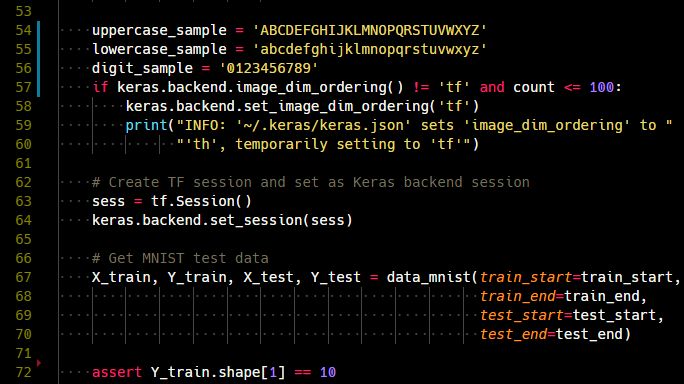
Hack
▎2. DejaVu Sans Mono
DejaVu 也是一款优秀的免费许可字体,来自 Bitstream Vera。能明显地区分0O和1lI。0与 Hack 相比,内部的点有点小,但总体上这个字体还是让人感觉舒适的。
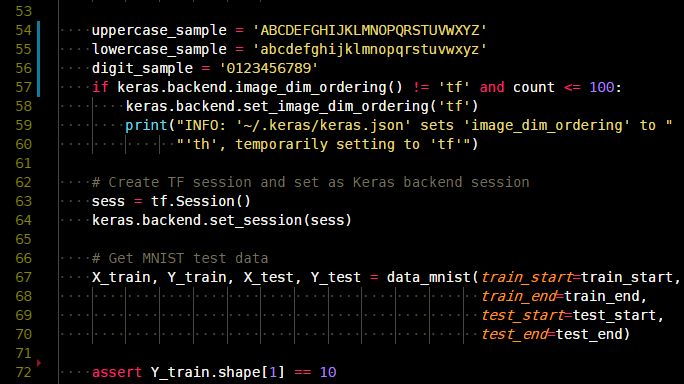
DejaVu Sans Mono
▎3. Monaco
OS X 之前的默认字体就是它,它的风格特殊,有种苹果味。
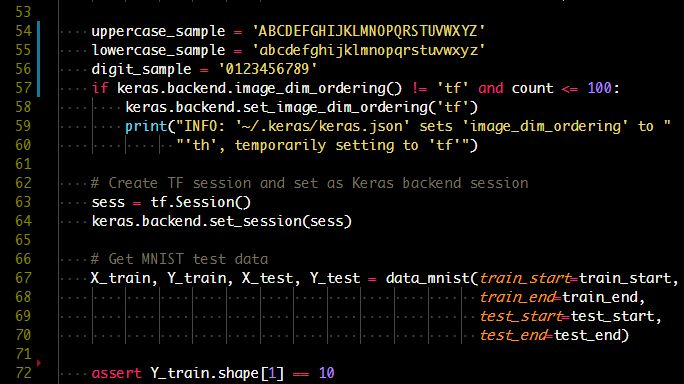
Monaco
▎4. Source Code Pro
Source Code Pro 由 Adobe 设计。整体而言,这种字体看起来比其他字体更清晰。
Source Code Pro
▎5. Menlo
Menlo 之前是 Xcode 中的默认字体,是 DejaVu Sans Mono 的衍生品。在 macOS High Sierra 中,默认字体已更改为 San Francisco Mono
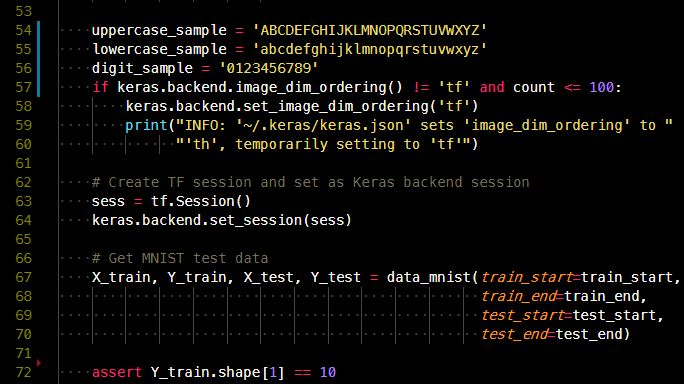
Menlo
▎6. Consolas
Consolas 是 Microsoft Visual Studio 的默认字体,随 Windows 一起提供。
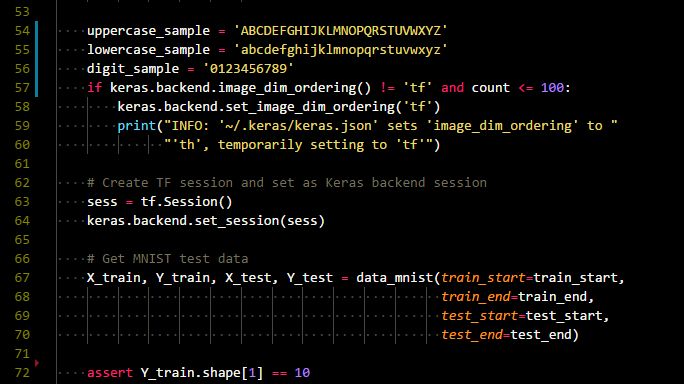
Consolas
▎7. Space Mono
一款优秀的等宽字体,由 Colophon Foundry 设计。
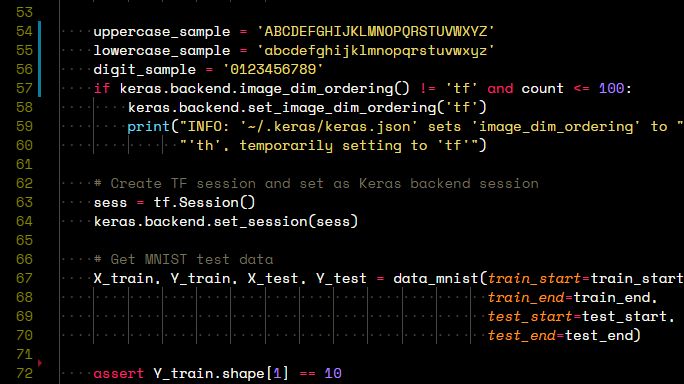
Space Mono
▎8. Anonymous Pro
这个字体给人一种古典打字机的感觉。
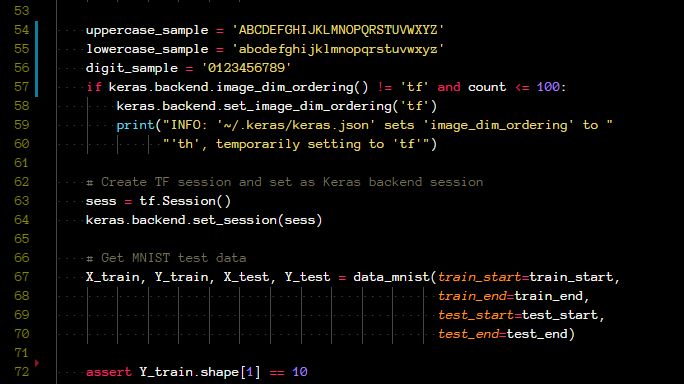
Anonymous Pro
▎9. IBM 3270
IBM 3270 基于 IBM 在 1971 年制造的 IBM 3270 终端中使用的字体,有种复古编程的味道。
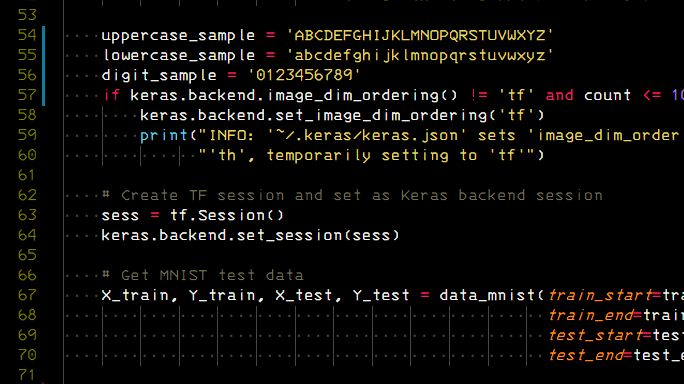
IBM 3270
▎10. Droid Sans Mono
这是为 Android 设计的一种字体,很漂亮,但是0和O并没有区分。
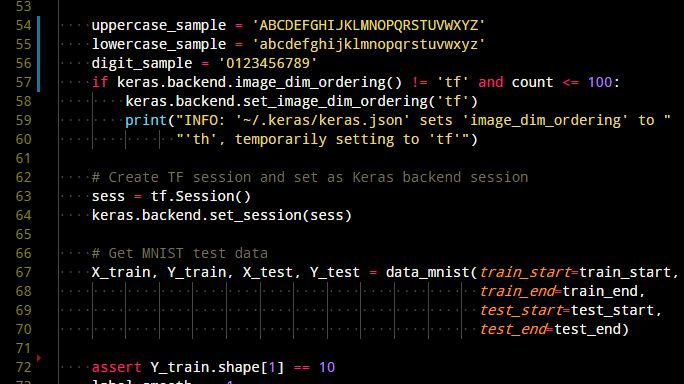
Droid Sans Mono